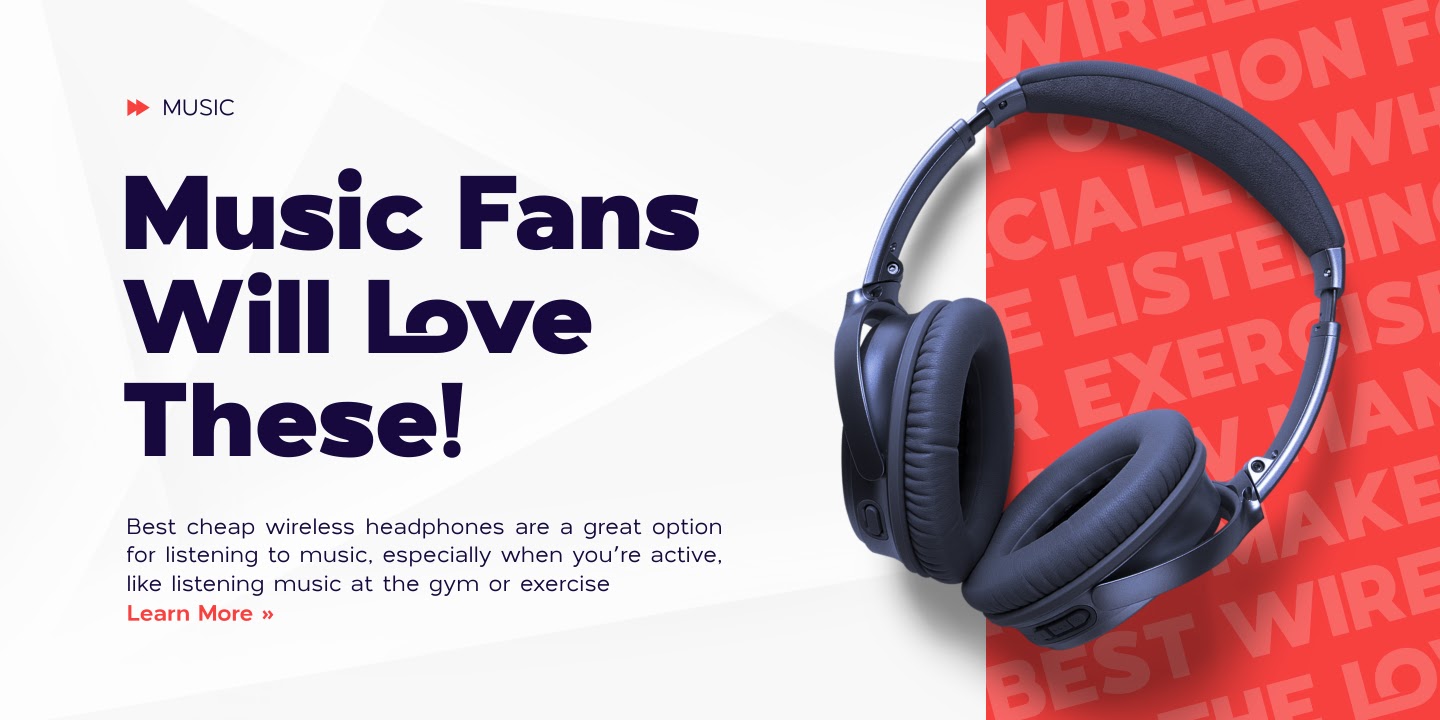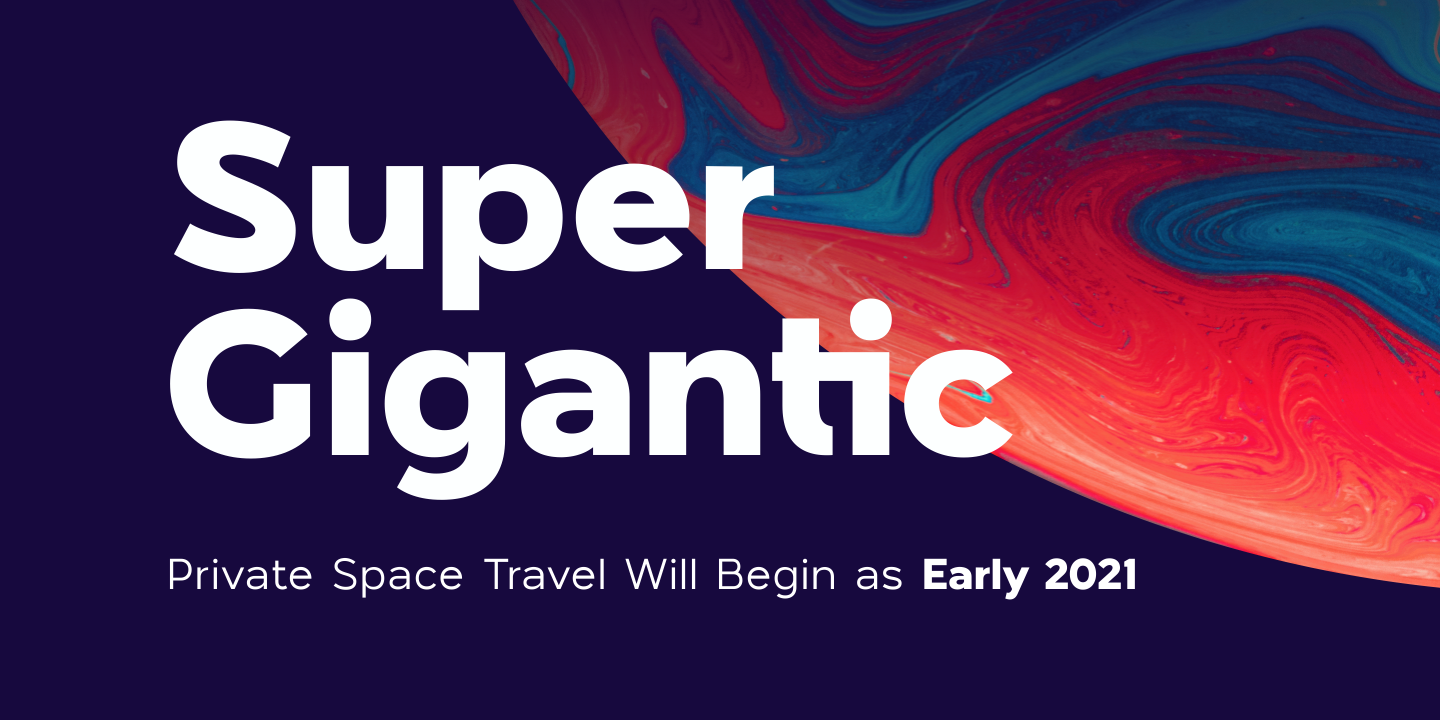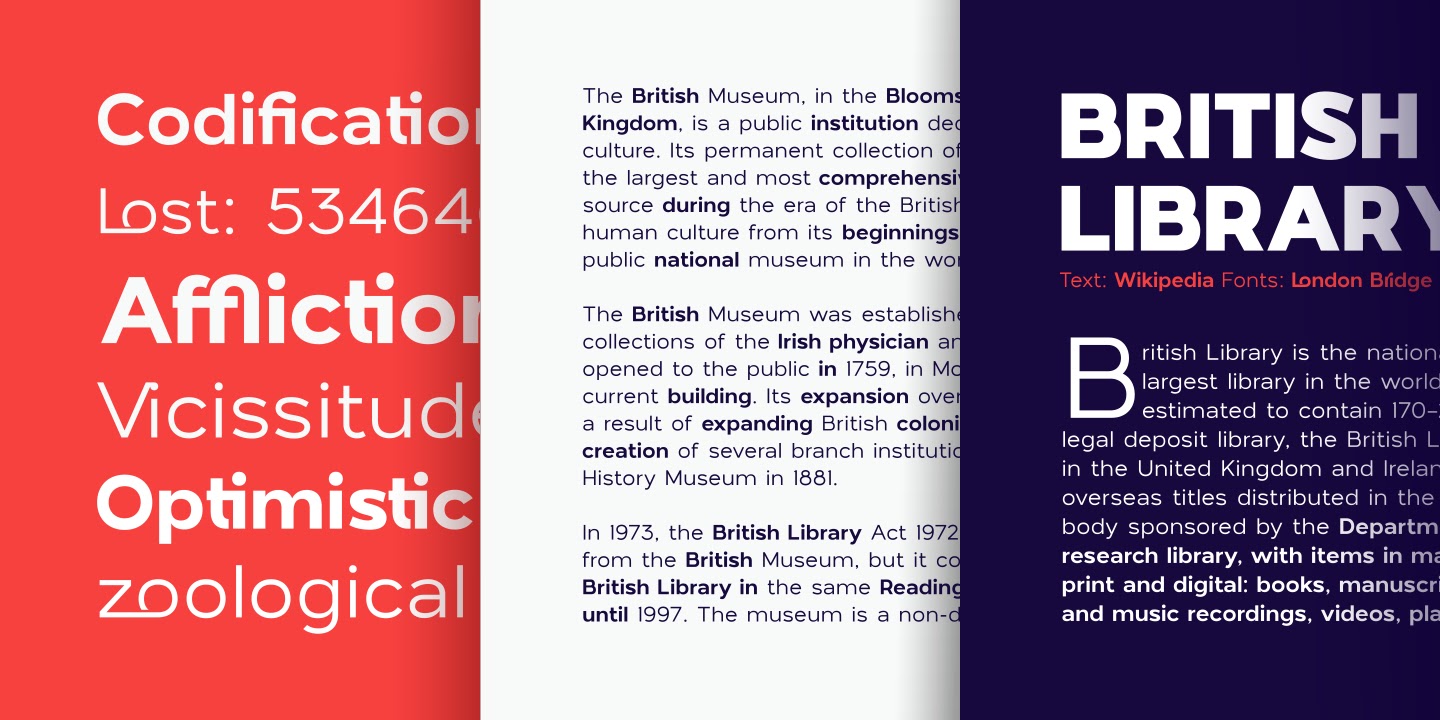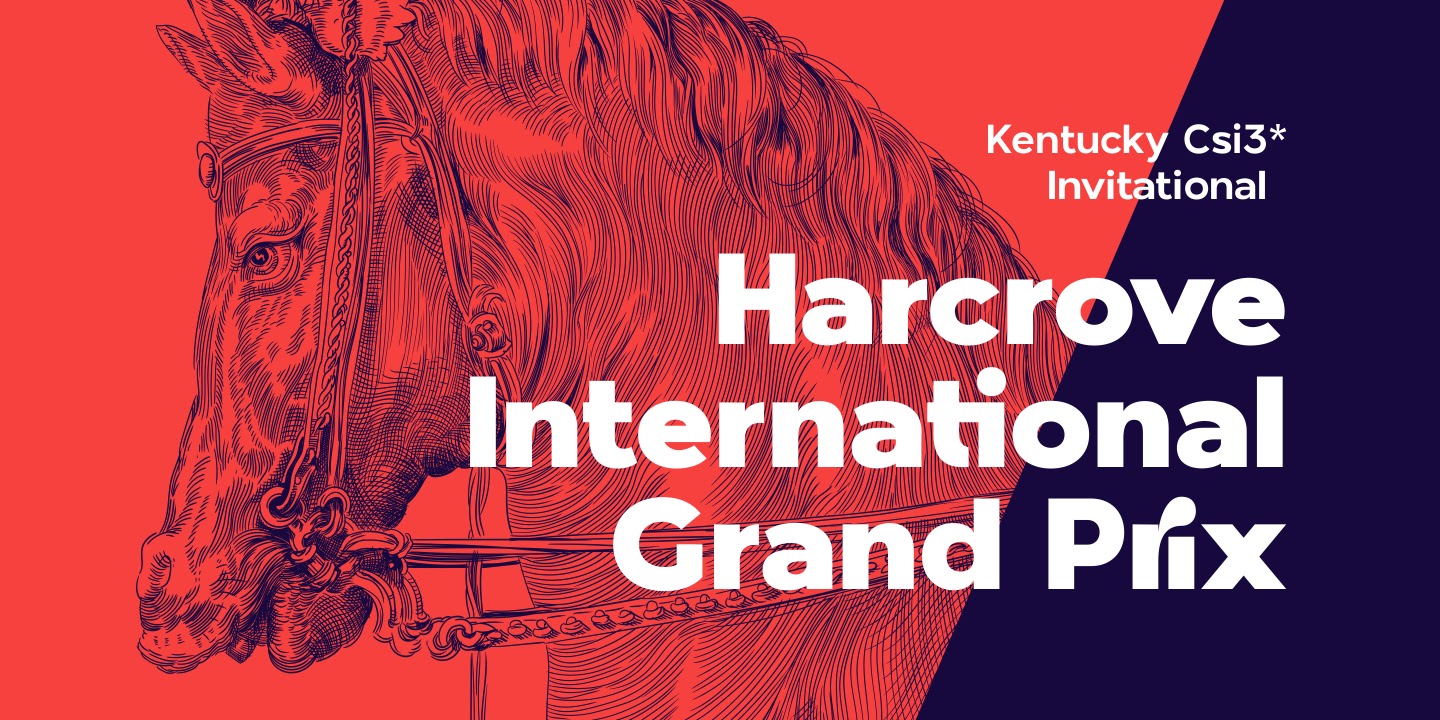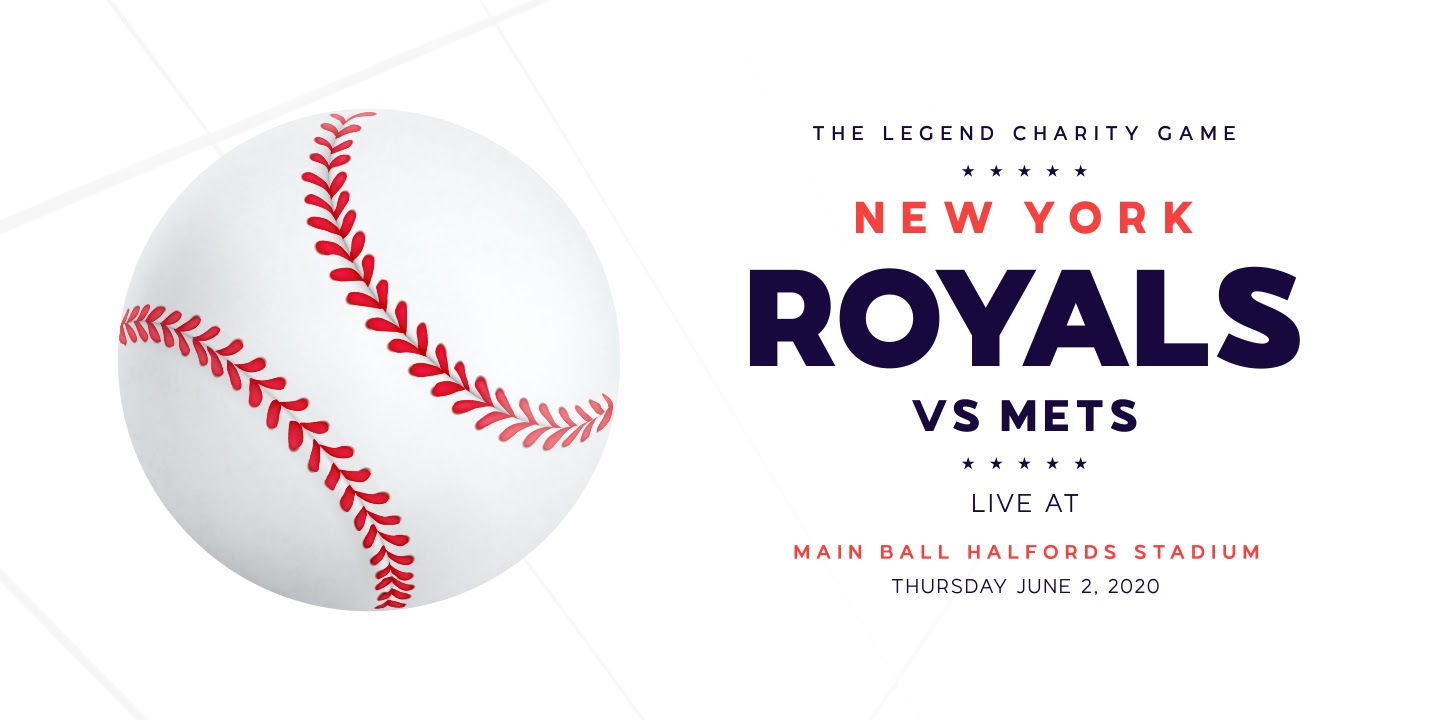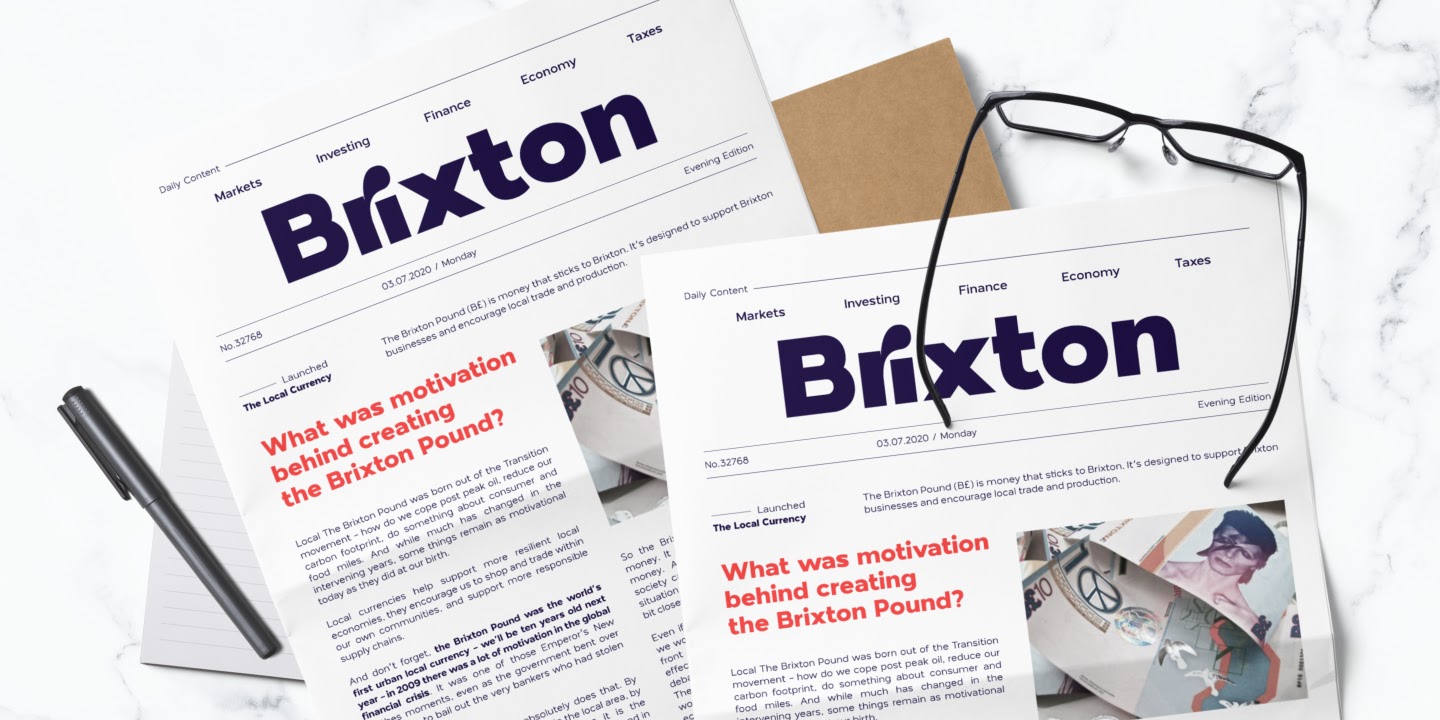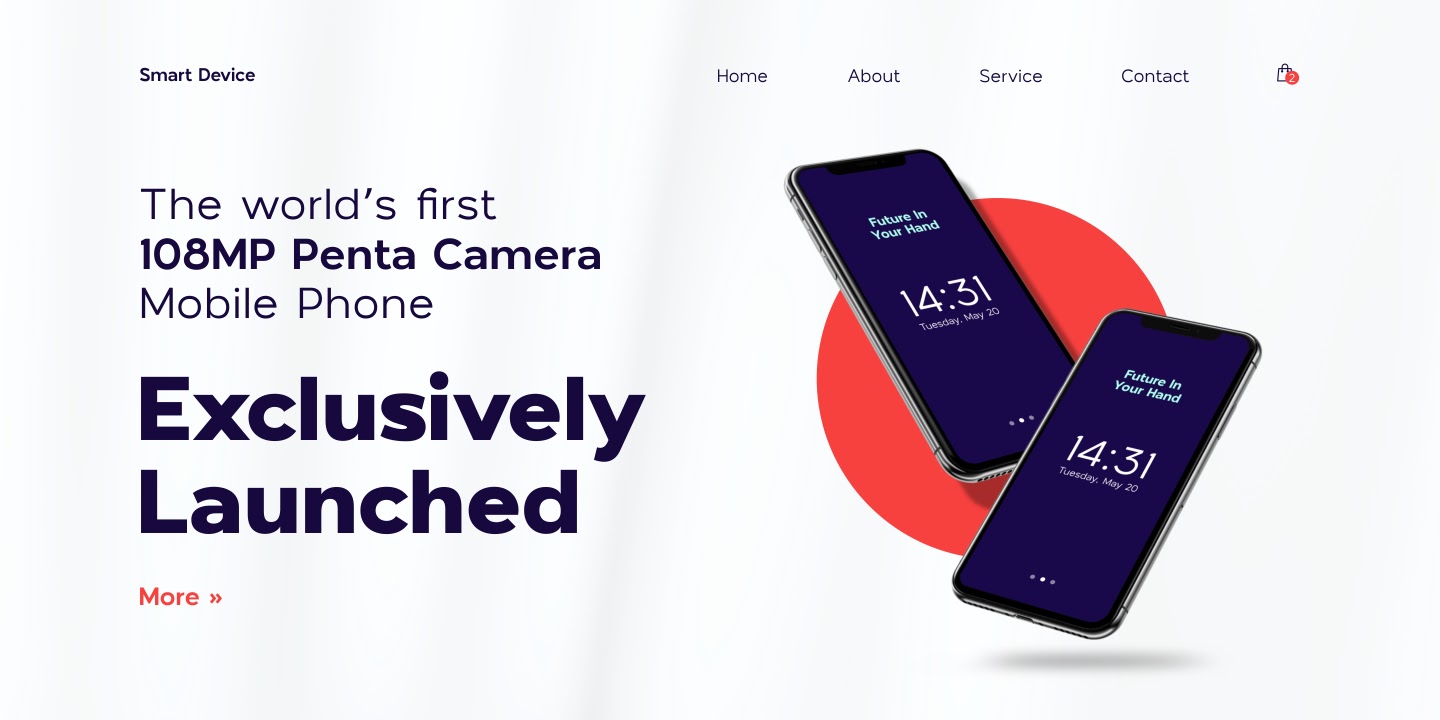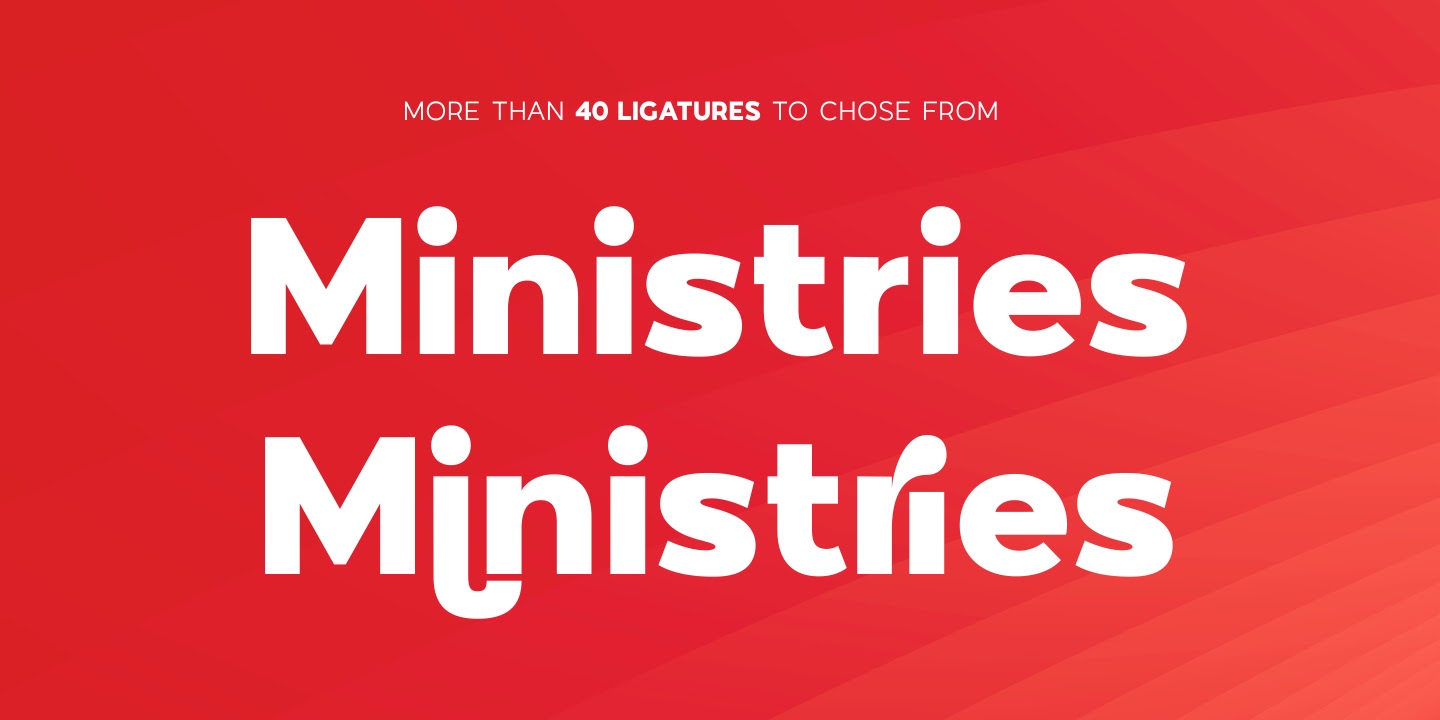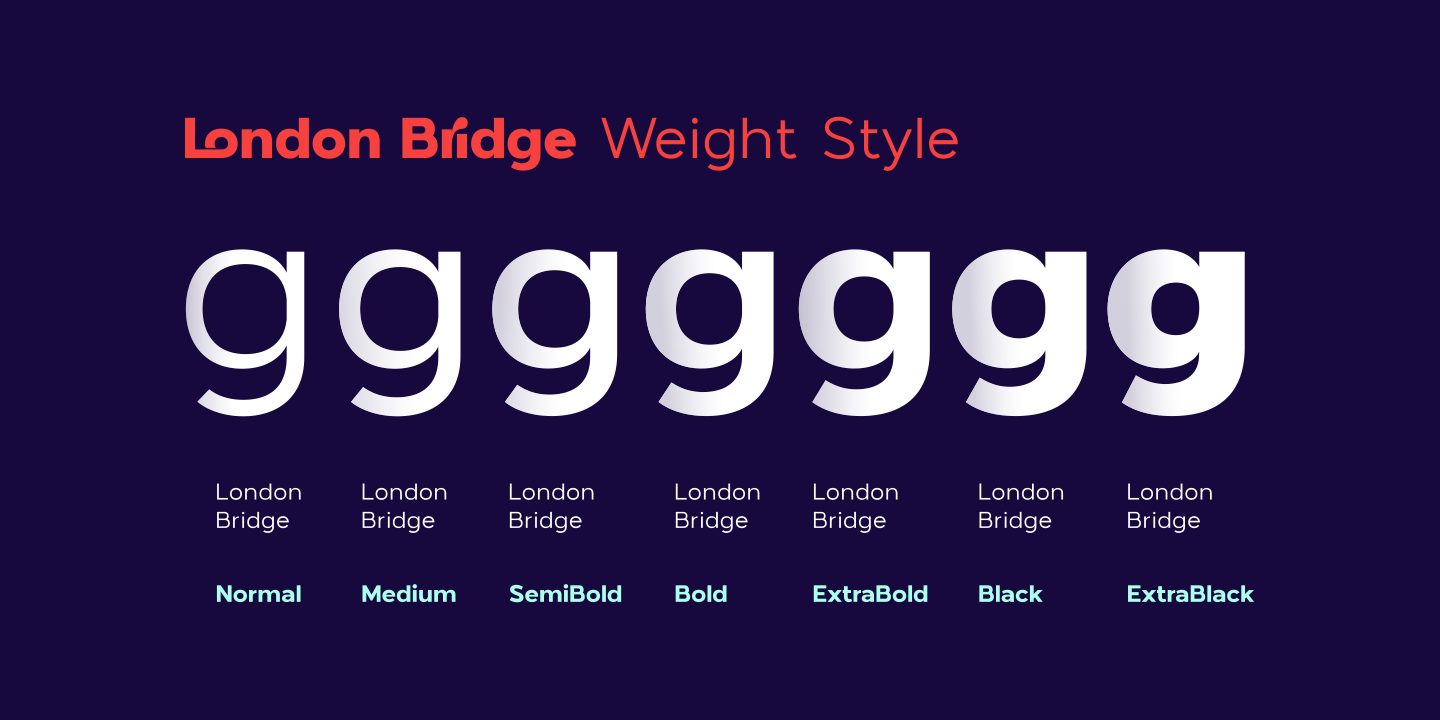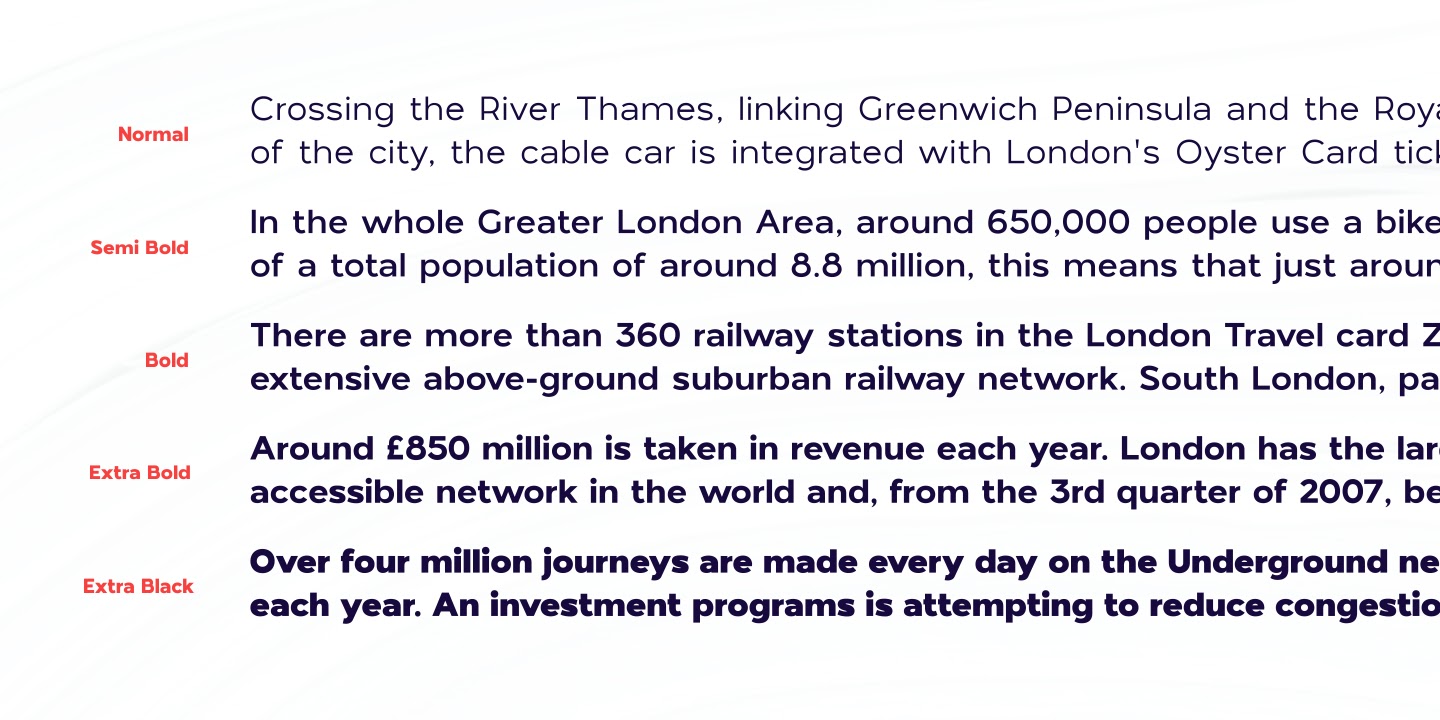
London Bridge là một Sans Serif hiện đại với nét đẹp và hình học. Nó có 7 kiểu. Mỗi kiểu bao gồm hỗ trợ ngôn ngữ mở rộng, phân số, thứ tự, chỉ số trên và hơn 30 chữ ghép. Được thiết kế với các tính năng OpenType mạnh mẽ, nó hoàn toàn phù hợp cho thiết kế đồ họa và bất kỳ mục đích sử dụng màn hình nào.